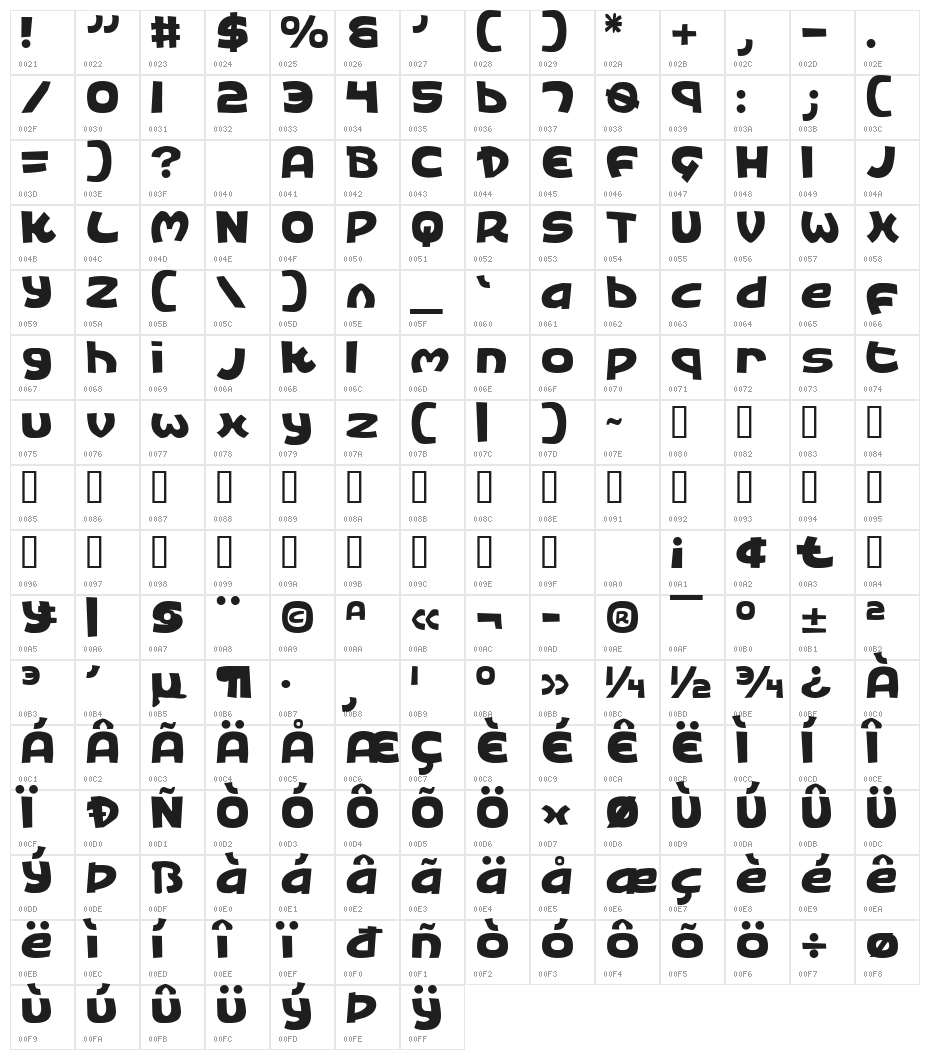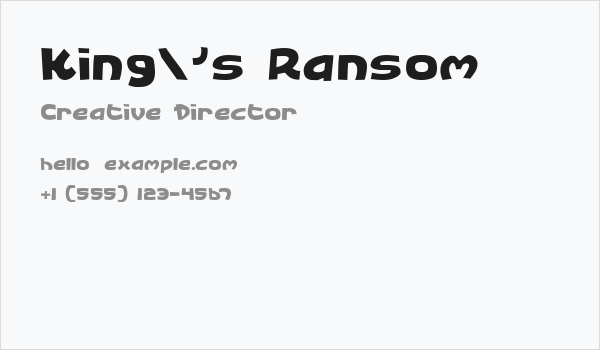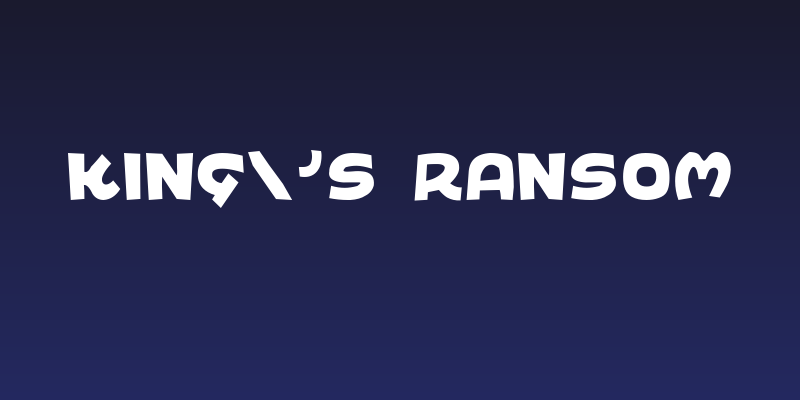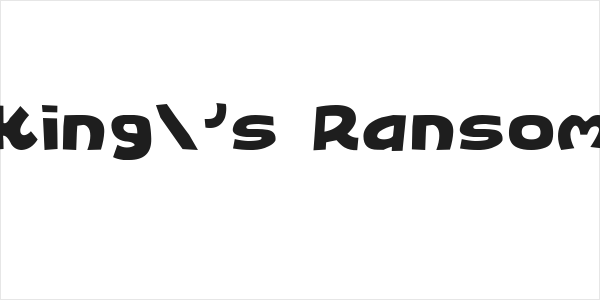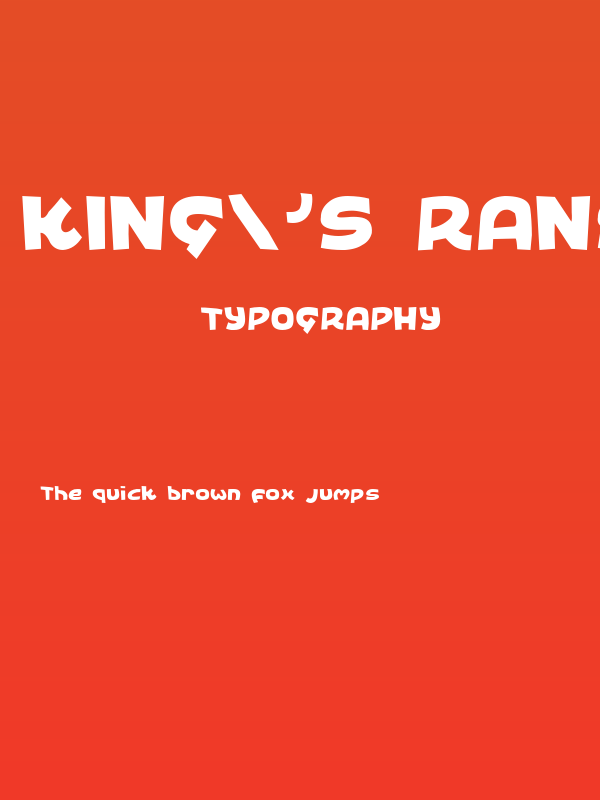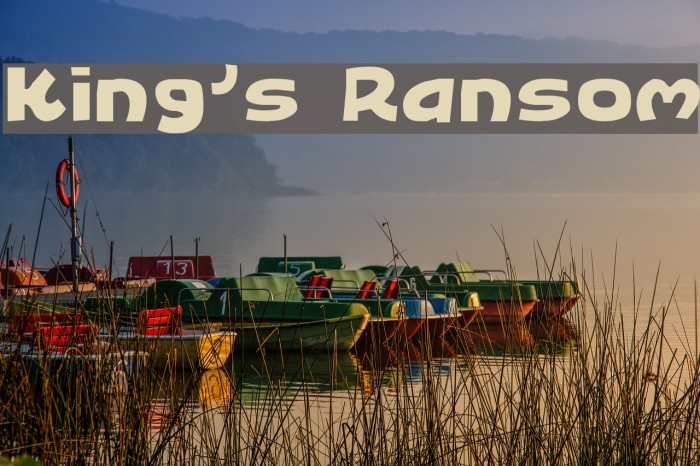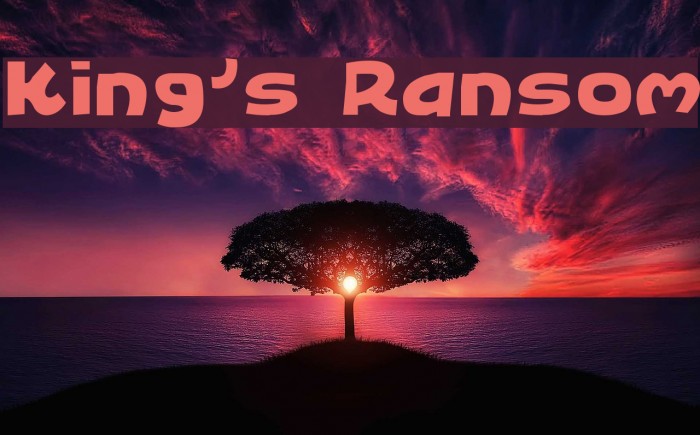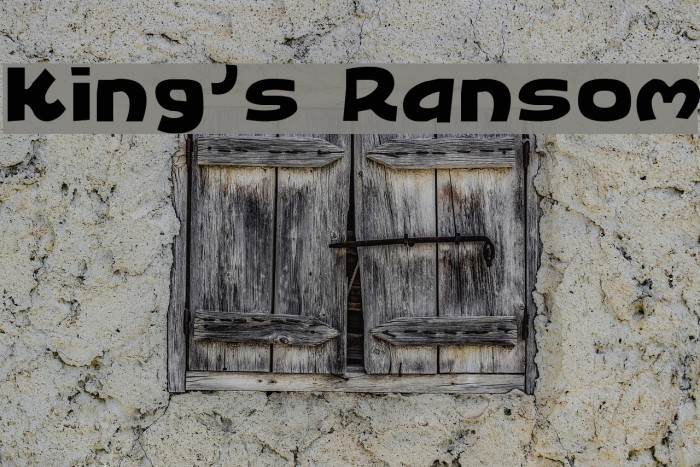
King's Ransom Font
Fonts by Daniel Zadorozny - www.iconian.com
| Gesamtstil | Playful, Quirky, Cartoonish |
| Vorgeschlagene Projekte | Ideal for children's books, comic strips, playful branding, and creative posters. |